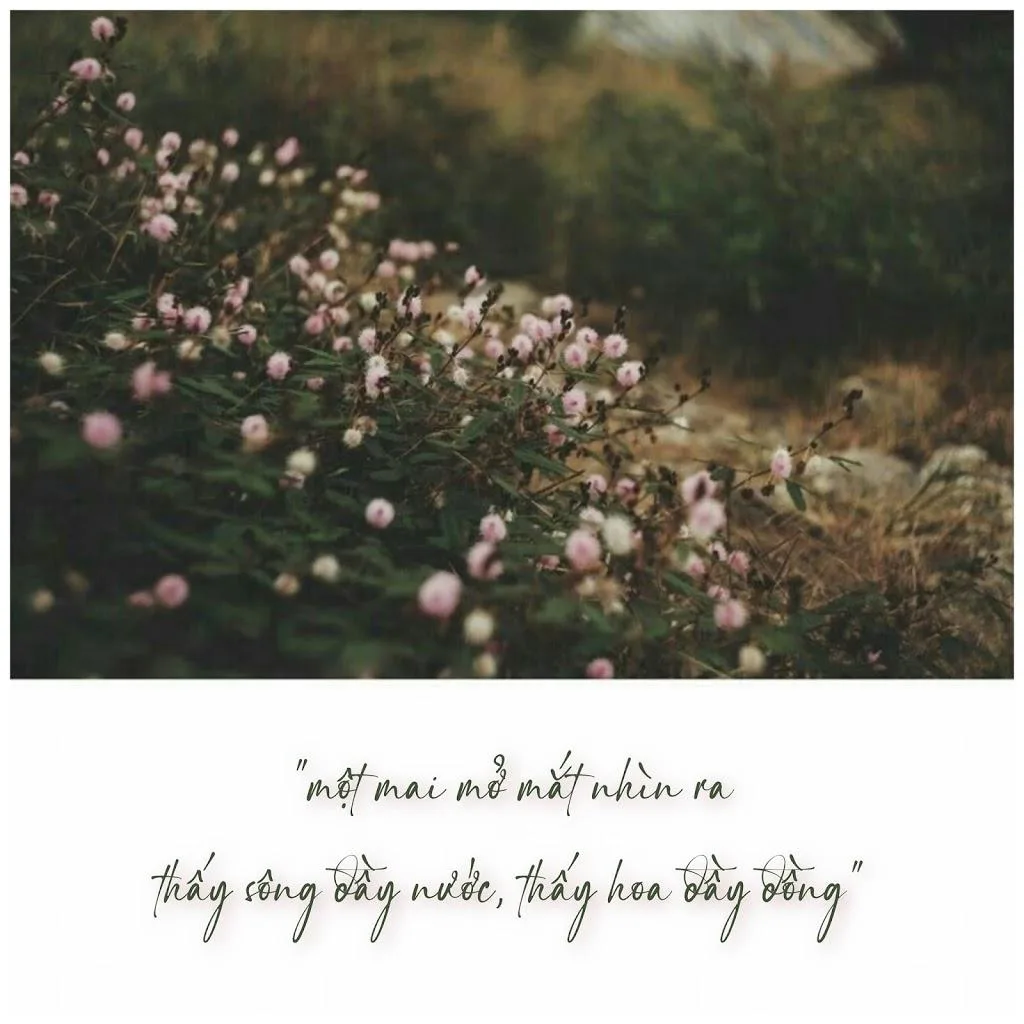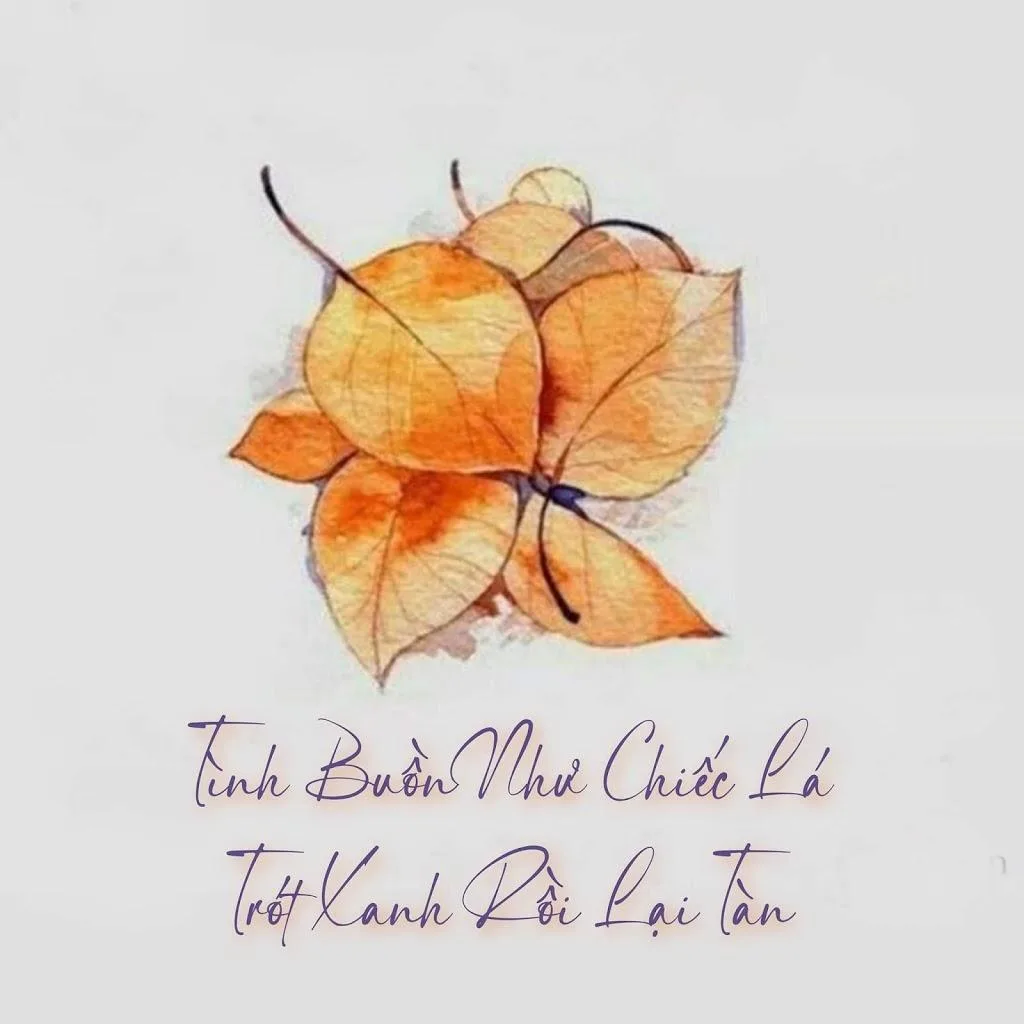
Tải Font SignRathi Việt hóa – Phông chữ ký siêu đẹp
Font SignRathi được sáng tạo bởi Dwi Ahidian và Việt hóa, đồng thời bổ sung quy tắc gõ bởi Đức Thủy. Đây là một font chữ ký độc đáo, mang đến sự tinh tế và chuyên nghiệp cho người sử dụng. Với nét chữ mảnh mai, thanh thoát và khả năng tùy biến linh hoạt, Fz SignRathi hứa hẹn sẽ tạo ấn tượng mạnh mẽ cho thương hiệu hoặc cá nhân của bạn.
Những điểm mới trong bản cập nhật V2 3.2023:
• Hệ thống quy tắc gõ đơn giản: Giúp dễ dàng sử dụng các ký tự mở rộng trên cả điện thoại và máy tính.
• Bộ ký tự thay thế phong phú: Cập nhật thêm 8 kiểu chữ, đáp ứng nhu cầu sáng tạo đa dạng.
Ứng dụng của font chữ ký SignRathi Việt hóa:
Font SignRathi Việt hóa có khả năng ứng dụng rộng rãi trong nhiều lĩnh vực, bao gồm:
Ứng dụng trong thiết kế:
• Logo và thương hiệu
• Thiệp mời, thiệp cưới
• Văn phòng phẩm
• Bài đăng mạng xã hội
• Quảng cáo, thiết kế sản phẩm, nhãn hiệu, nhiếp ảnh, watermark
Ứng dụng cá nhân:
• Tạo chữ ký độc đáo
• Thể hiện cá tính và khẳng định bản thân
• Nâng cao giá trị thẩm mỹ
Ưu điểm của SignRathi:
• Nét chữ thanh thoát, tinh tế, mang tính thẩm mỹ cao
• Phong cách hiện đại, chuyên nghiệp, phù hợp với xu hướng thiết kế mới
• Khả năng tùy biến linh hoạt, đáp ứng nhu cầu sáng tạo đa dạng
• Dễ sử dụng, phù hợp cho cả người mới bắt đầu
Quy tắc gõ các ký tự mở rộng trong font SignRathi:
Ký tự thường:
• Bao gồm 7 bộ ký tự thường (a-z) mô phỏng nét viết tay tự nhiên.
• Gõ kết hợp chữ cái thường với số từ 1 đến 7 (ví dụ: a1, b2, c3…).
Bạn có thể thử nghiệm và kiểm tra trực tiếp các kiểu chữ bằng cách gõ các tổ hợp như: a1, a2, a3…
Ký tự hoa:
• Bộ ký tự hoa (A-Z) thanh đậm, tạo điểm nhấn cho chữ ký
• Gõ kết hợp chữ cái hoa với số 1 (ví dụ: A1, B1, C1…)
Ký tự gạch chân:
• 5 ký tự gạch chân (a-z) mô phỏng nét chữ viết tay thanh mảnh
• Gõ kết hợp chữ cái thường với số 0 (bạn gõ: a0, b0, c0, d0, e0)
• Cách gõ để thể hiện chữ như ô bên dưới: C1hữ a0 K1ý Siêu b0 Đẹp Gạchc0 Chân Cd0ũng X1e0ịn